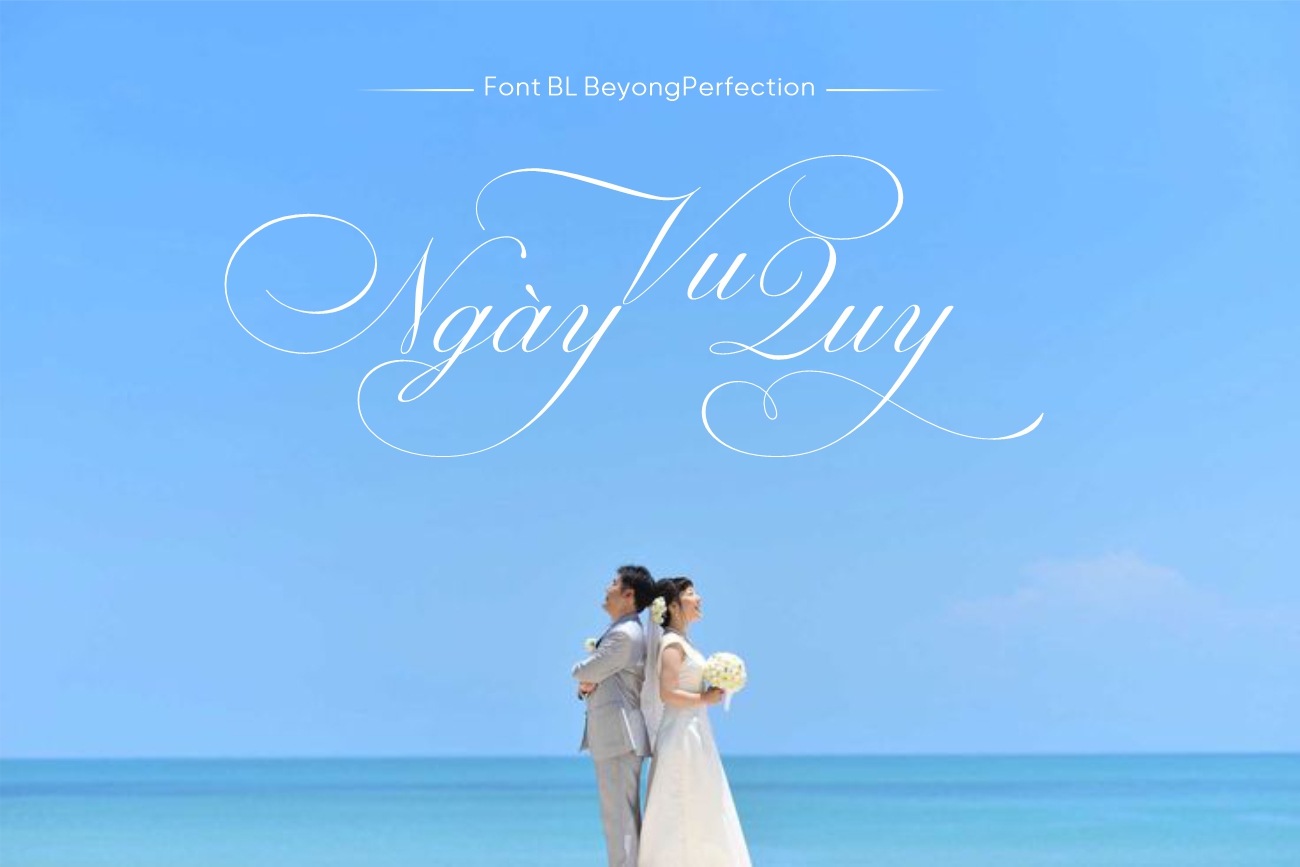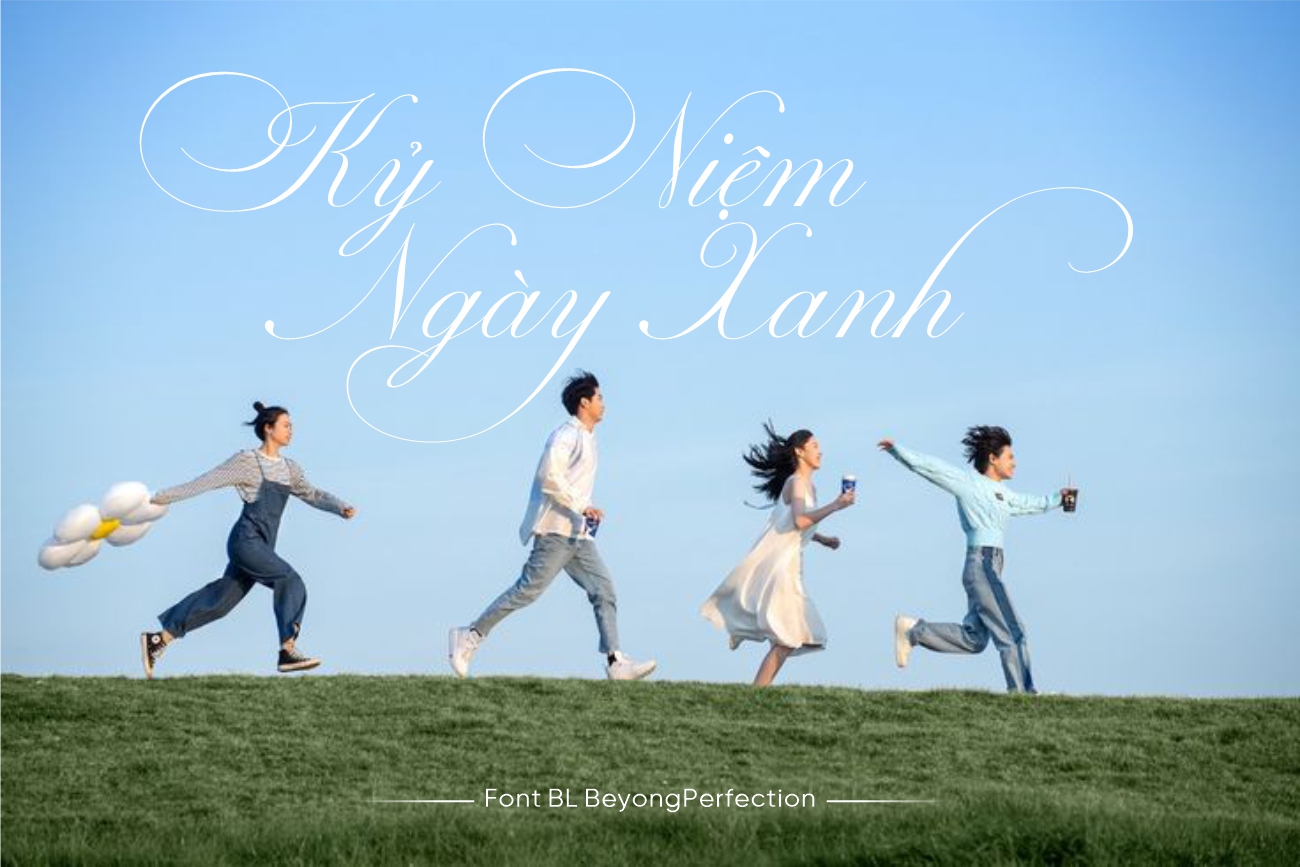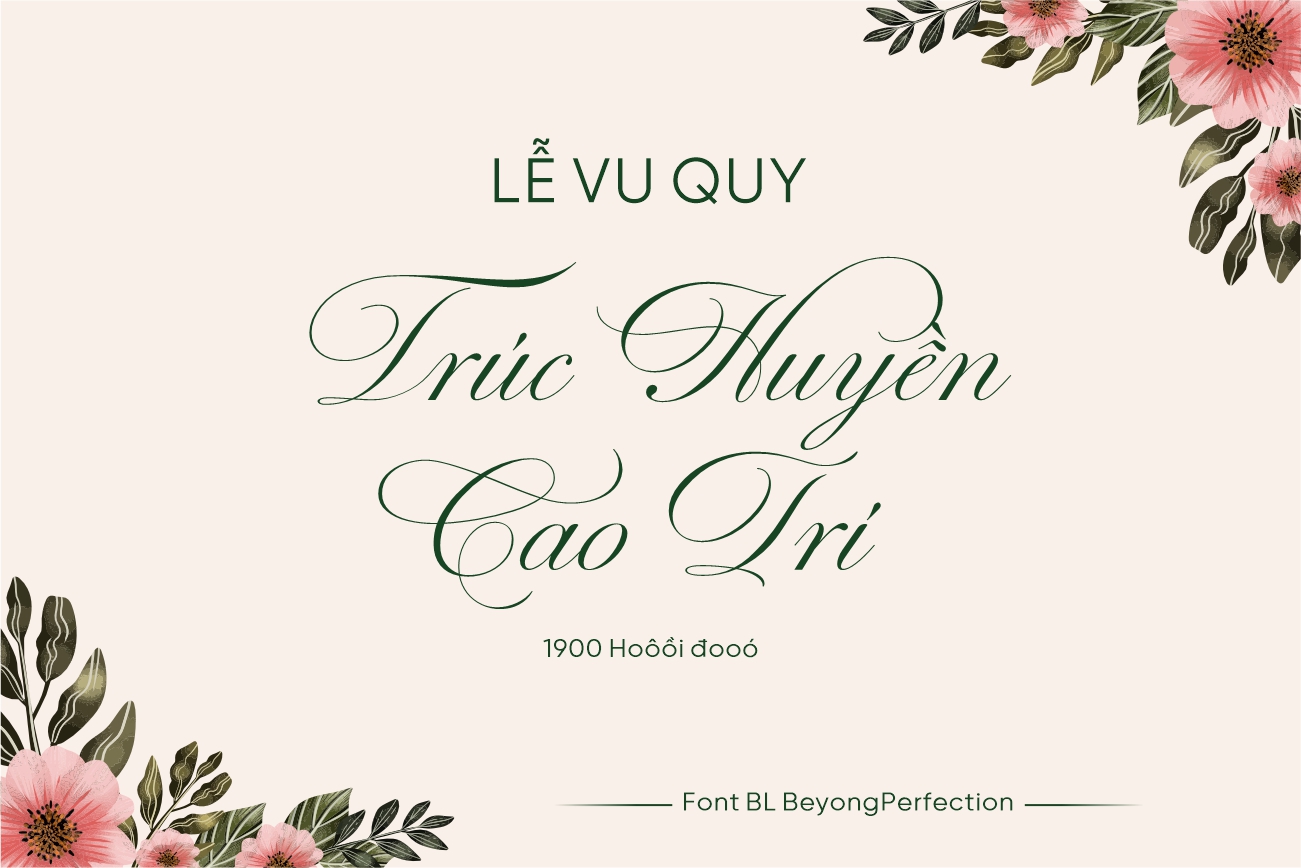
Phông chữ nét mảnh cho đám cưới BL BeyongPerfection Việt Hóa
Font BL BeyongPerfection là một kiểu chữ mang phong cách script hiện đại kết hợp calligraphy, mềm mại nhưng sang trọng, rất thích hợp cho những thiết kế cần sự tinh tế.
Phong cách: Thuộc nhóm modern script / calligraphy, với những đường nét uốn lượn uyển chuyển như bút mực, gợi cảm giác lãng mạn và nghệ thuật.
Đặc điểm nổi bật:
Nét chữ bay bổng, thanh thoát nhưng vẫn rõ ràng, dễ đọc.
Có nhiều ký tự thay thế (alternates) và ligatures, giúp thiết kế đa dạng, sống động hơn.
Tạo cảm giác sang trọng, tinh tế, phù hợp cho các thiết kế cao cấp.
Ứng dụng:
Thiệp cưới, thiệp mời, bìa album ảnh.
Logo thương hiệu thời trang, mỹ phẩm, trang sức.
Bao bì sản phẩm cao cấp, card visit nghệ thuật.
Typography trang trí, poster lãng mạn.